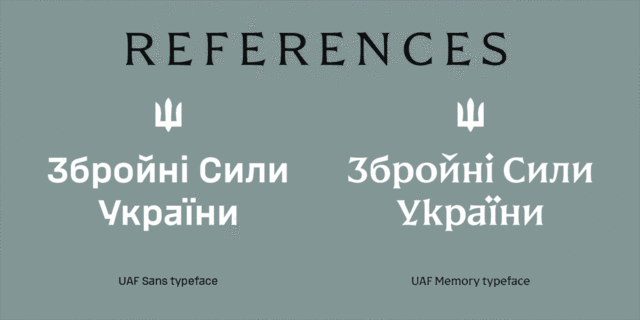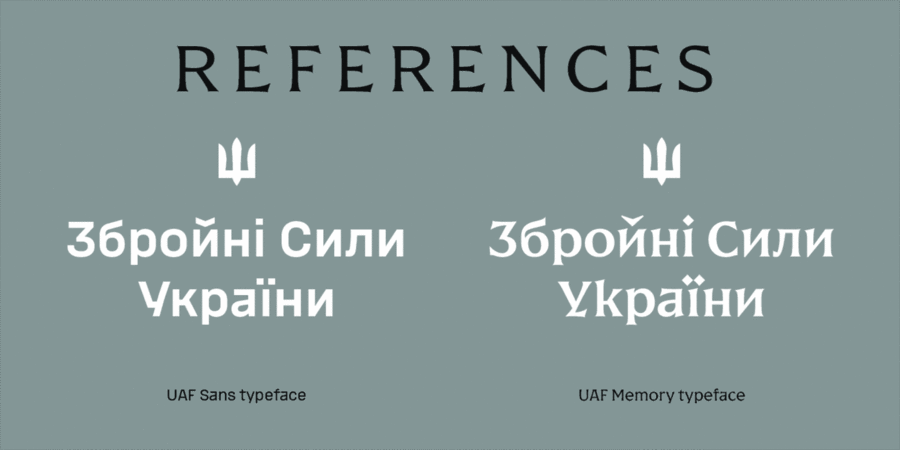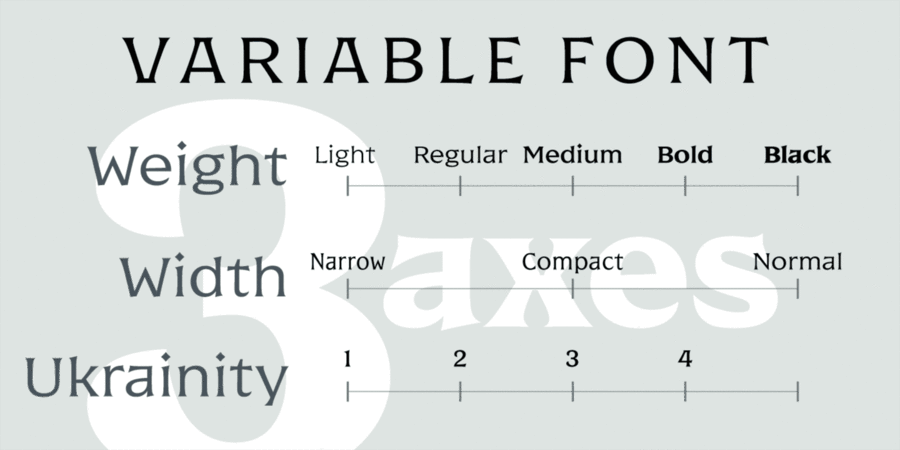
Шрифтове сімейство UAF Memory є продовженням роботи над брендуванням Збройних Cил України і слідує загальному дизайну UAF Sans. Деталі шрифту походять від традиційних монументальних написів. Він призначений в першу чергу для вшанування загиблих українських героїв на меморіальних дошках і військових могилах. Безкоштовний для комерційного та некомерційного використання.
Асоціації з сімейством шрифтів UAF MemoryОсобистість і характер гарнітури:
аристократичний, історичний, королівський, пафосний, традиційний, унікальний, кам'яний, імперський, гострий, легендарний, різкий, ностальгічний, гордий, переконливий, твердий, стійкий, авторитетний, цікавий, дзвінкий, гуманітарний, колючий, старовинний, старомодний, фантастичний, релігійний, біблійний, церковний, чіткий, серйозний, жорсткий, залізний, сталевий, незвичайний, карбований, важливий, монументальний, архітектурний, впевнений, яскравий, помітний, амбітний, експериментальний, активний, героїчний, лицарський, сміливий, золотий, християнський, сакральний, самобутній, колоритний, сильний, грубий, кристальний, екстравагантний, мотивуючий, творчий, потужний, гучний, агресивний, експресивний, ремісничий, значний, суворий, мужній, військовий, крутий, незграбний, рубаний, ігровий, ефектний, якісний, культурний, добірний, благородний, гармонійний, елітний, дорогий, розкішний, красивий, ювелірний, майстерний, естетичний, художній, знаменитий, дорогоцінний, оригінальний, багатий, міський, виразний, артистичний, сексуальний, характерний, прекрасний, динамічний, класичний, урочистий, тріумфальний, звитяжний, епічний, римський, консервативний, освічений, кінематографічний, древній, войовничий, хоробрий, бравий, темпераментний, добротний
геральдика, епос, музей, меморіал, пам'ятник, надгробок, скульптура, історія, король, меч, антикваріат, карти, література, мистецтво, художник, архітектура, банкнота, монета, пригоди, гра, віскі, Трофей, нагорода, замок, гроші, захід сонця, концерт, лицар, обладунки, тату, татуювання, меню, туризм, Біблія, вечір, сувенір, кіно, казка, сувій, Чарівна казка, таверна, легенда, комп'ютерна гра, дракон, філософія, реконструкція, прапор, ніж, ремесло, війна, рок, зброя, краса, преміум, готель, шоколад, прикраса, ювелір, золото, коштовності, музика, опера, ресторан, розкіш, театр, годинник, бутік, алкоголь, коньяк, вино, літопис, горілка, бібліотека, культура, гравюра, церква, храм, монастир, влада, коваль, тютюн, бій, сир, камінь, шолом, ром, релігія, люкс Гарнітура має ознаки стилів: